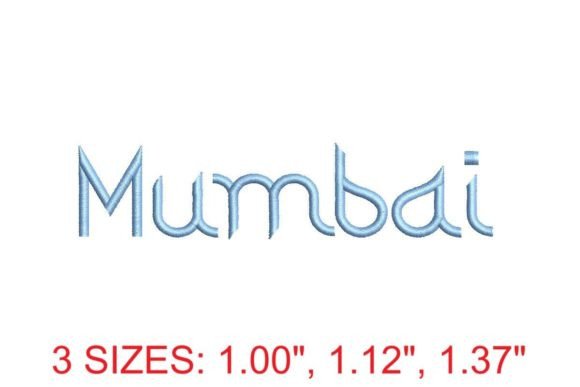
Mumbai Embroidery Font
Việc tìm kiếm các thành phần thiết kế phù hợp có thể là một thách thức, nhưng Mumbai Embroidery Font cung cấp một bộ sưu tập đặc biệt giúp nâng tầm công việc của bạn ngay lập tức.